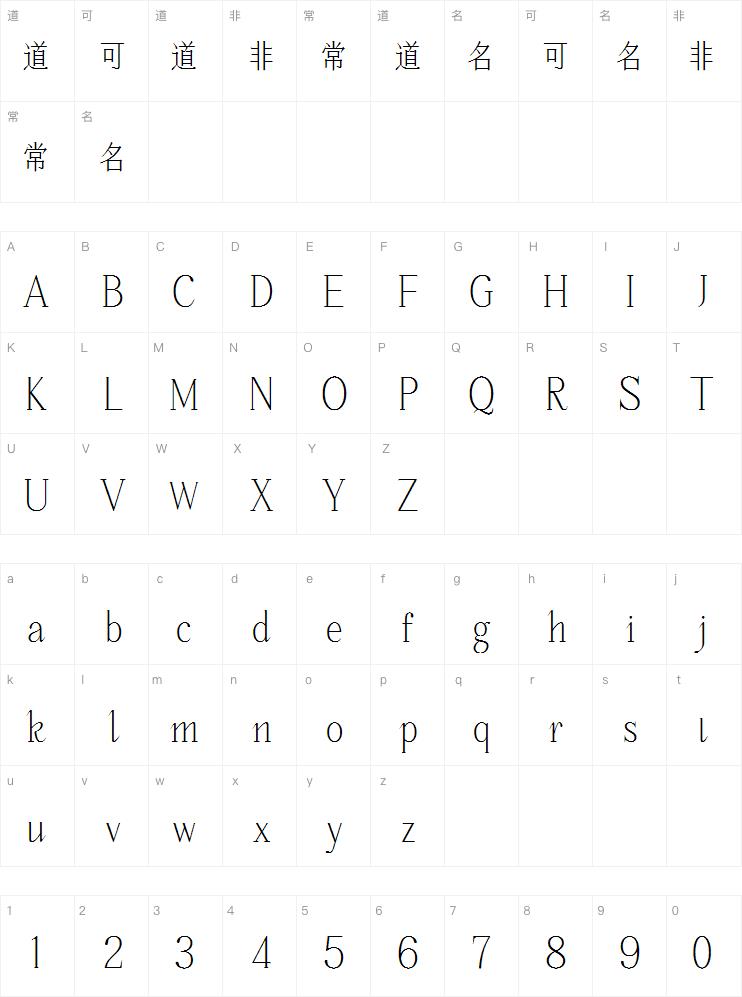
字魂吴文化博物馆苏绣体
字魂吴文化博物馆苏绣
字魂吴文化博物馆苏绣体,是字魂为吴文化博物馆量身定制的一款字体。这款字体从苏绣非遗技艺中汲取灵感,将代表性的绣针造型融入笔画,字形刚柔并济,灵动秀雅。字形的横笔中,还化用了吴文化博物馆藏的苏绣云肩——《四合如意》这一作品中的线条,使其横画笔直平整,但末端上翘,恰似绣娘用绣针挑线的动作,活灵活现。西文字体部分在纤细的衬线体基础上,增加以手写痕迹,使西文字体更多一份温度与人文主义。而字母尖角处设计成圆润且利落的线条弧度,使这款定制字体的西文也能展现出独特的东方气韵。该字体适用于宣传海报、周边产品、美妆、文旅等场景和行业中。
字魂吴文化博物馆苏绣体